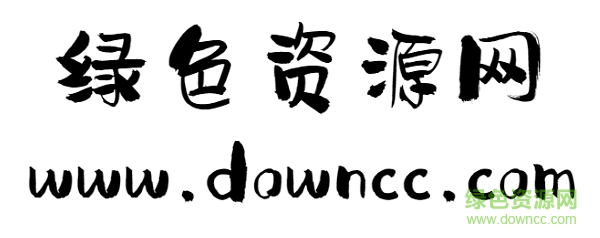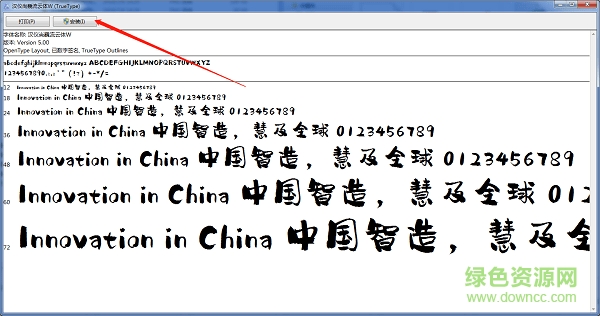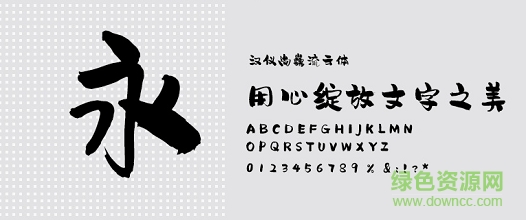
漢儀尚巍流云體w字體粗狂大氣,渾厚的筆鋒讓字體整體偏粗,適用于文章中較醒目的標(biāo)題或者是其他的界面,同時(shí)喜歡書(shū)法的用戶(hù)也可用來(lái)練習(xí)字體哦,喜歡的用戶(hù)快來(lái)綠色資源網(wǎng)下載吧!
漢儀尚巍流云體字型巍峨挺拔,筆畫(huà)蒼勁有力,整體效果非常出色,讓人一眼就可以感受到它的存在,適合應(yīng)用于藝術(shù)設(shè)計(jì)、廣告宣傳設(shè)計(jì)、網(wǎng)頁(yè)設(shè)計(jì)等領(lǐng)域!